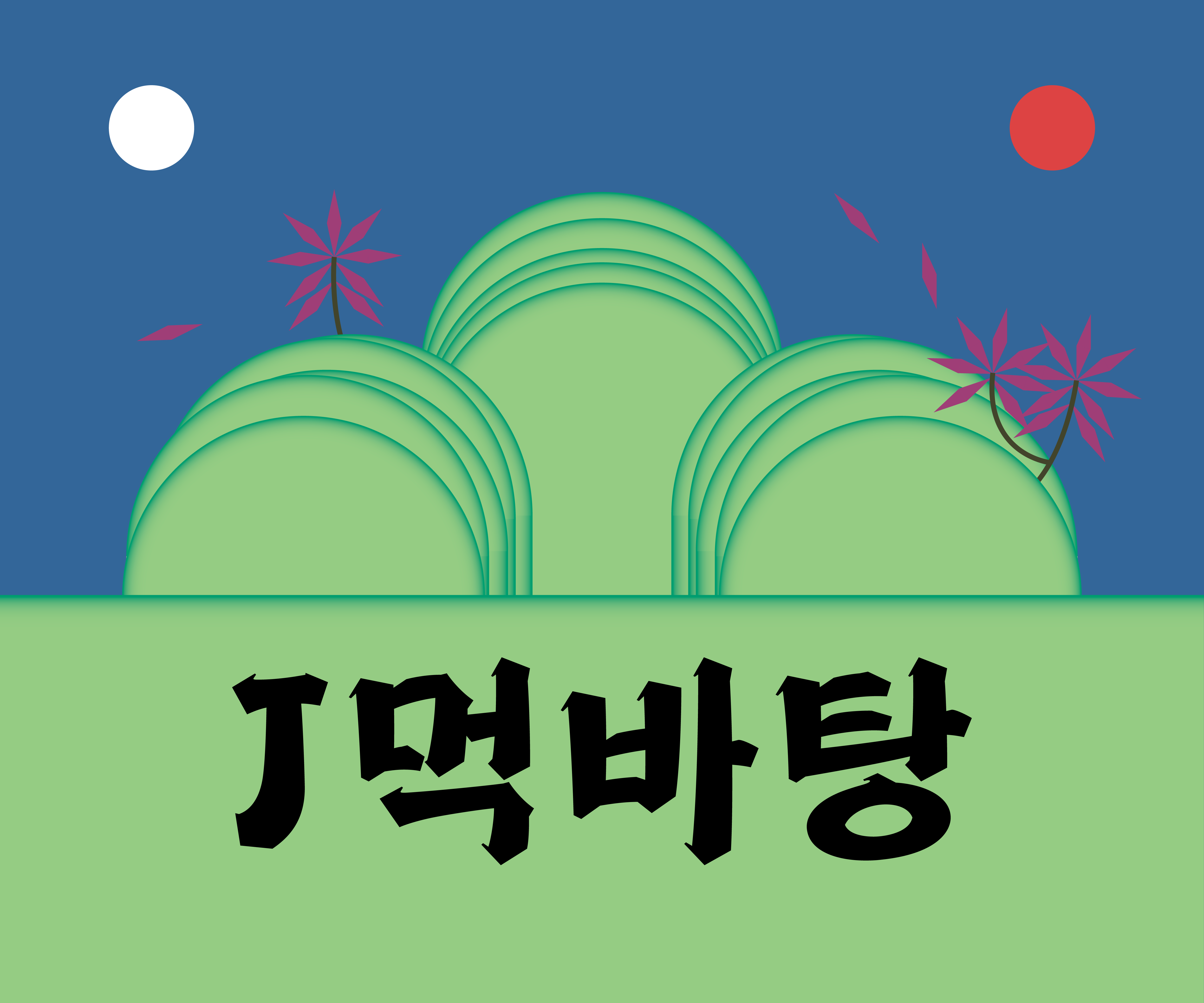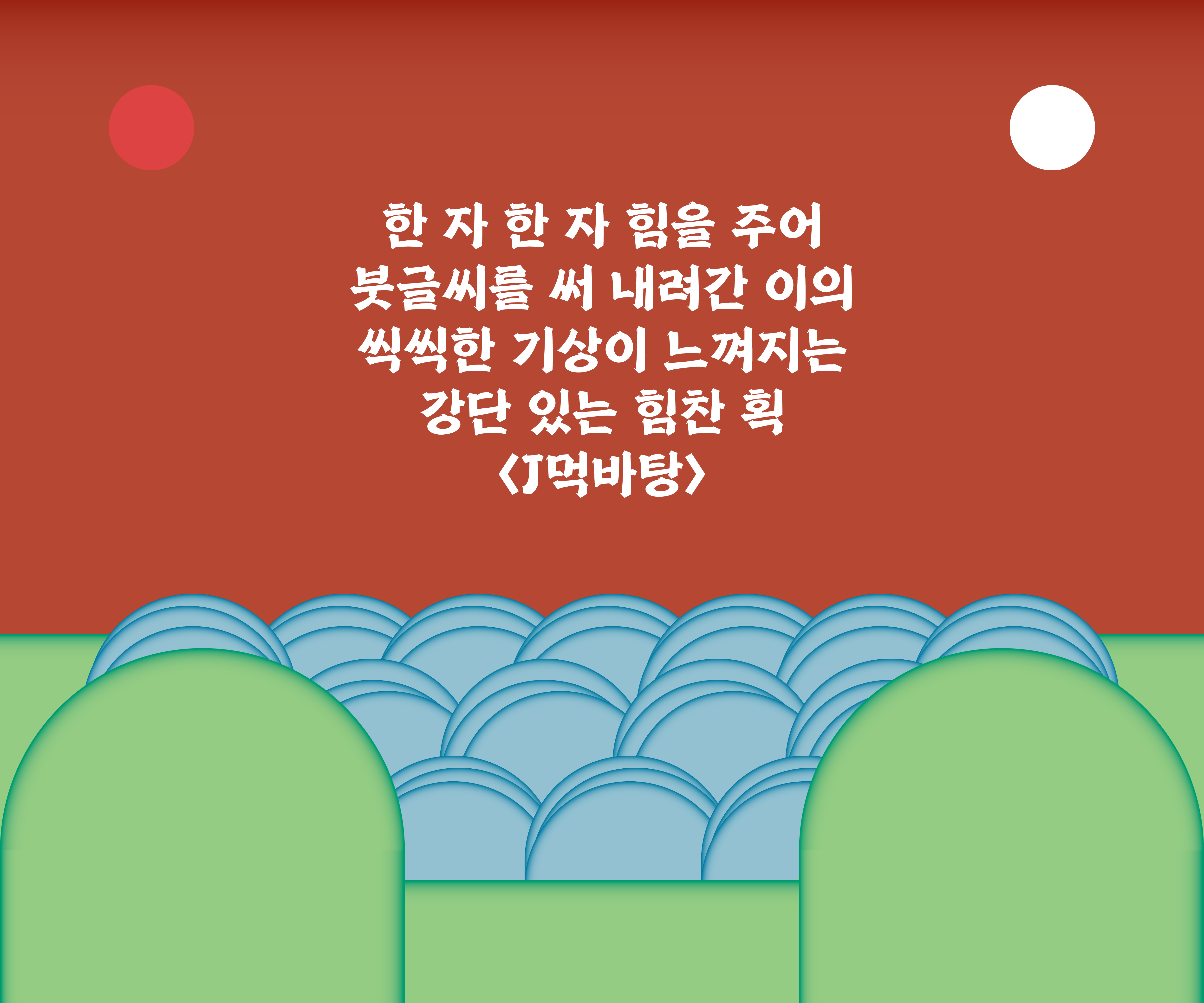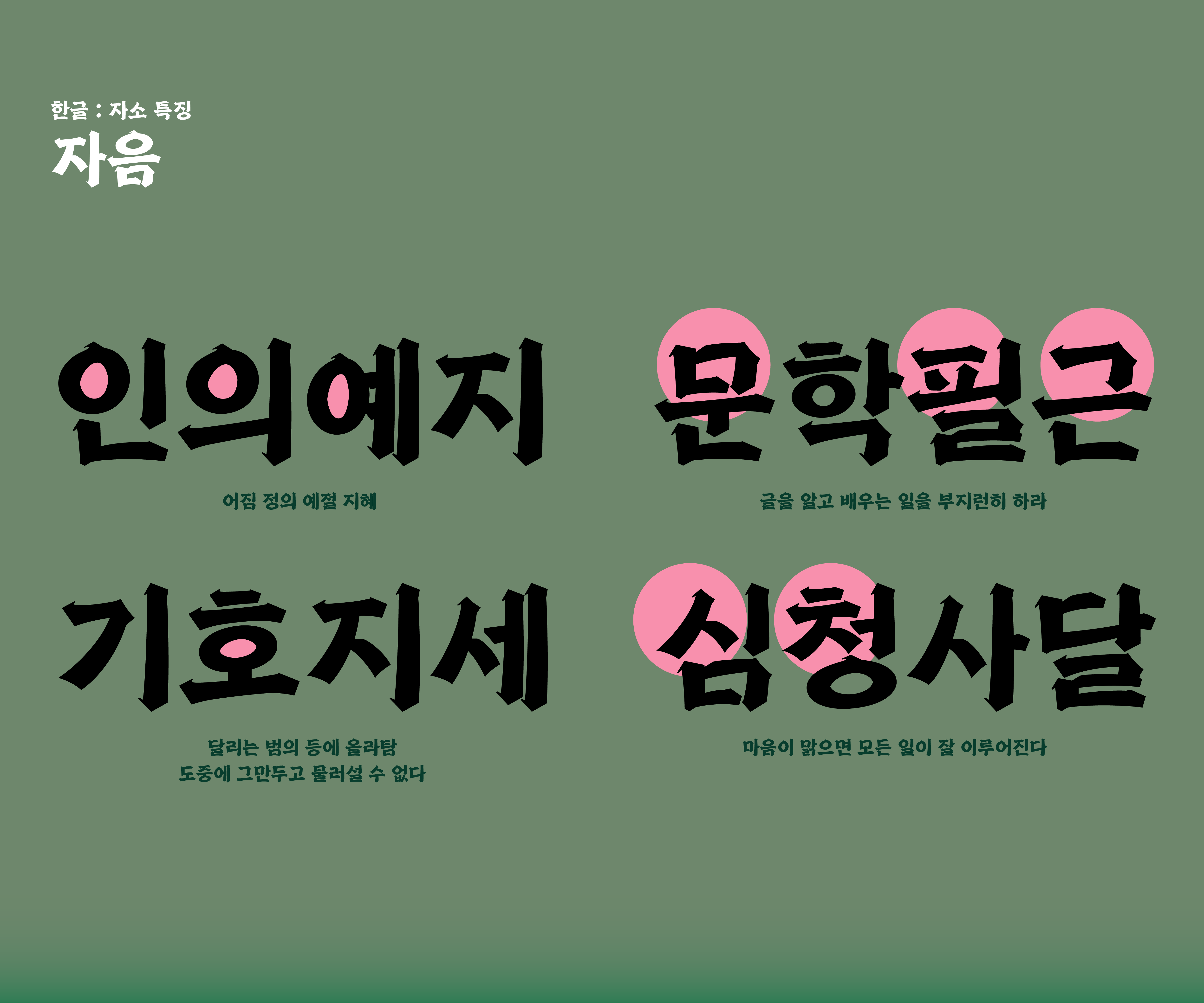
J먹바탕
• 푸른 소나무는 한겨울에도 푸름을 잃지 않는다.
폰트 설명
한자의 레퍼런스를 기반으로 한글에서도 같은 인상을 표현해 보고자 기획한 제목용 서체입니다. 강단 있는 획에서는 한 자 한 자 힘을 주어 붓글씨를 써 내려간 이의 씩씩한 기상이 느껴집니다. 동양적인 뉘앙스와 강인함 그리고 묵직한 무게를 가진 서체 <J먹바탕>. 글자의 재료인 '먹' 이 머금은 이미지와 물성을 그대로 담아 <먹바탕> 이라는 이름으로 선보입니다.